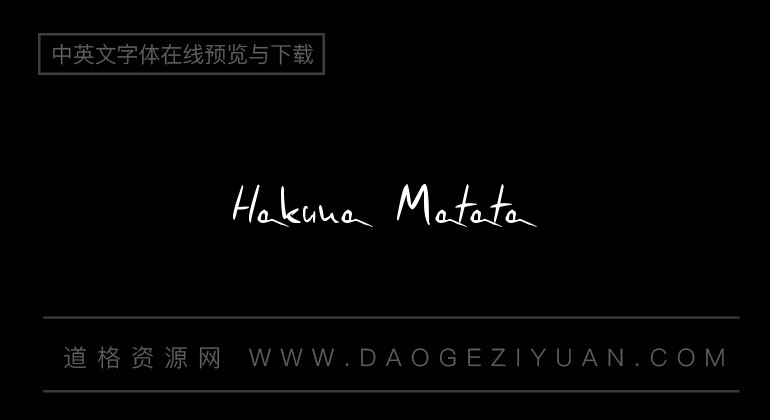
Hakuna Matata 是一种手写风格的字体,它的名字来自于斯瓦西里语,意思是“无忧无虑”。这个字体的设计灵感来自于非洲文化,特别是斯瓦希里语和马赛语的书写风格。 Hakuna Matata 字体的特点是字母形状不规则,线条柔和,给人一种随意自然的感觉。它的设计者将字母中的一些元素做成了类似于动物的形状,比如“a”的下部分像一只小鸟,而“g”的下部分像一只狗。 这个字体非常适合用于具有非洲主题的设计,比如旅游海报、手册、标志等等。它也非常适合用于带有轻松、愉快、放松的主题,因为它的名字就是“无忧无虑”。内容介绍
Hakuna Matata是一款非常不错的手写艺术字体,具有很好的视觉感,适合于文化类的宣传设计、商业类品牌的广告和产品包装设计以及个性化文字排版等较多场景。